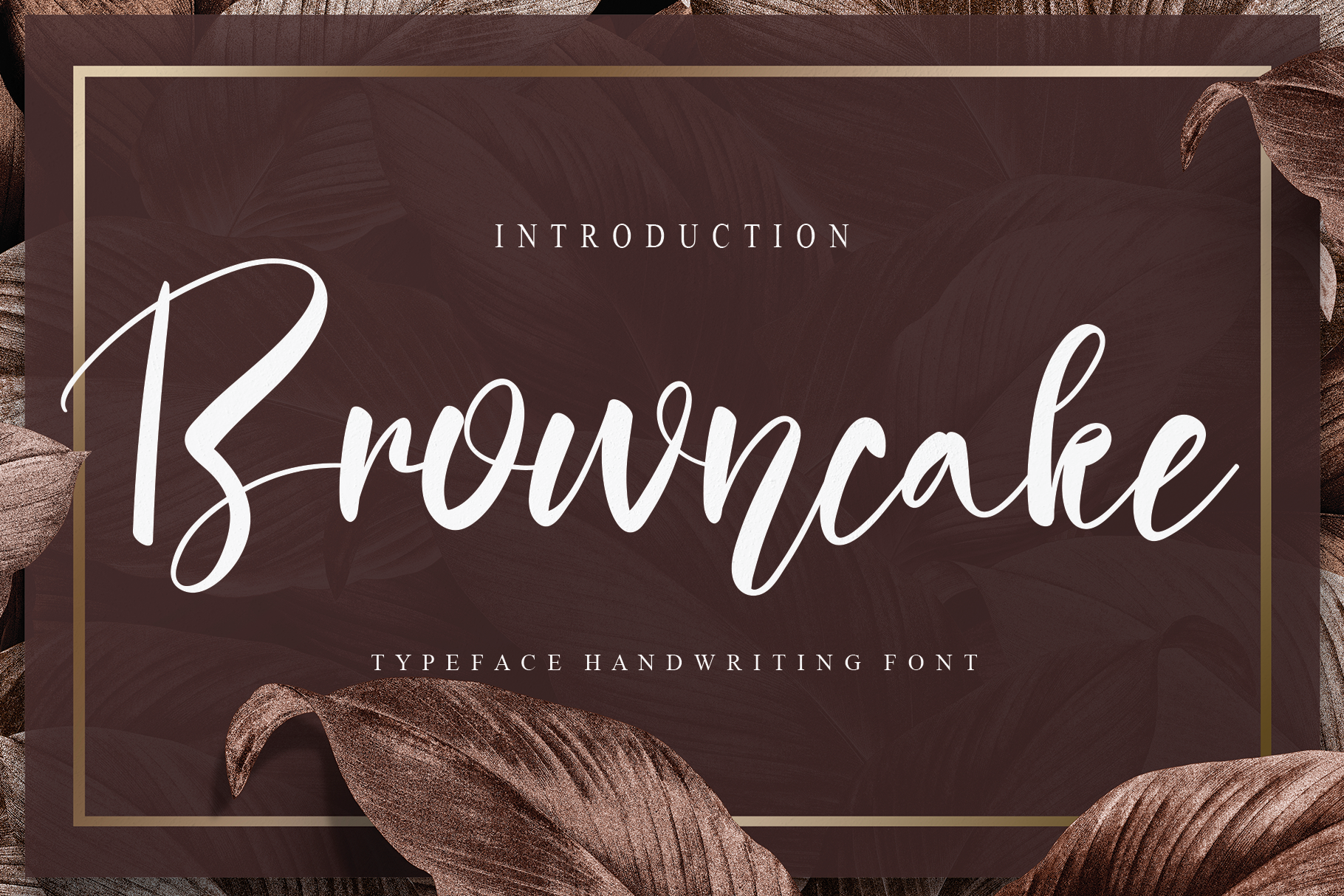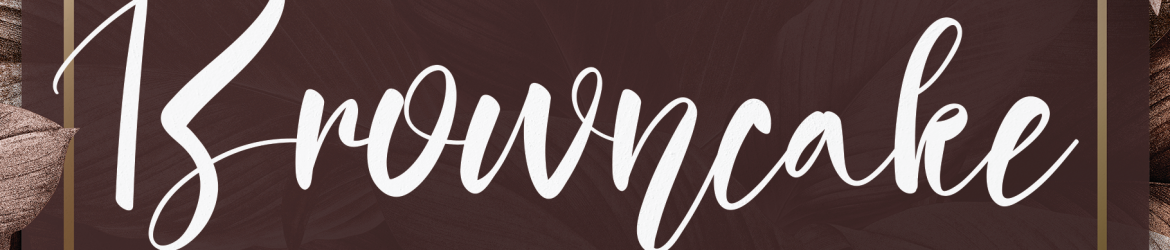
Esta é uma fonte escrita a mão elegante, perfeita para tornar seus designs ainda mais inovadores. Criada pelo designer creativeletter, ela traz um toque delicado e sofisticado que se destacará em qualquer projeto visual. Seja você criando cards de visita personalizados ou adesivos de aniversário, esta fonte escrita a mão oferece uma expressão única e única para seu design. Explore sua incrível capacidade de adaptabilidade ao explorar diferentes texturas e sentimentos que ela pode transmitir em seus trabalhos. A Browncake Font, disponível na categoria de fonts escritas a mão, é um investimento que não só melhorará o aspecto visual do seu projeto, mas também dará vida à sua mensagem através de uma representação artística única.